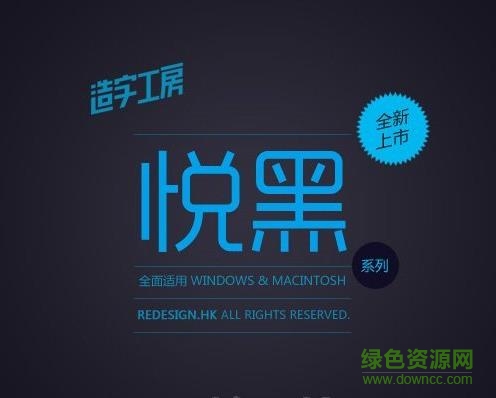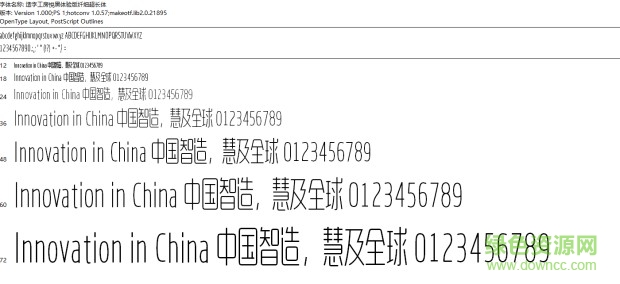
造字工房悅黑字體筆畫設(shè)計(jì)自然美觀,字形簡約,曲線優(yōu)美,具有較大范圍的應(yīng)用空間。適用于高端時尚品牌產(chǎn)品的形象設(shè)計(jì)與推廣。
來自造字工房的悅黑系列字體,本字體包共有8款字體,字體非常的美觀、大方!是用于長體,細(xì)體,纖細(xì)體設(shè)計(jì)方面的字體